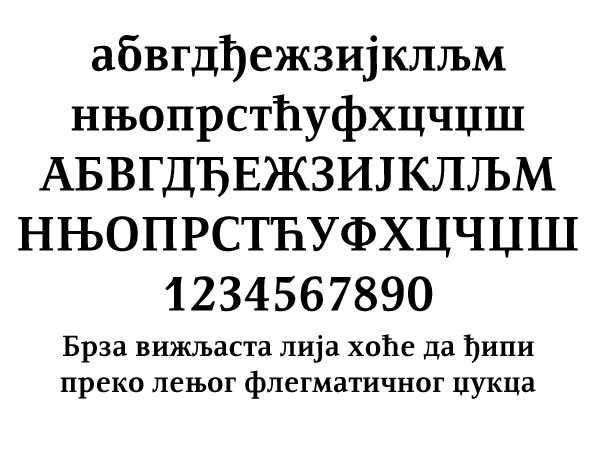
Ресавска БГ
Фамилија Ресавска БГ састоји се из следећа 4 фонта:
Ресавска БГ је серифно, књижно писмо, погодно за различите намене и широки круг корисника. Фонтови садрже слова српске ћирилице, основне латинице, знаке интерпункције и специјалне знаке потребне за слагање текста.